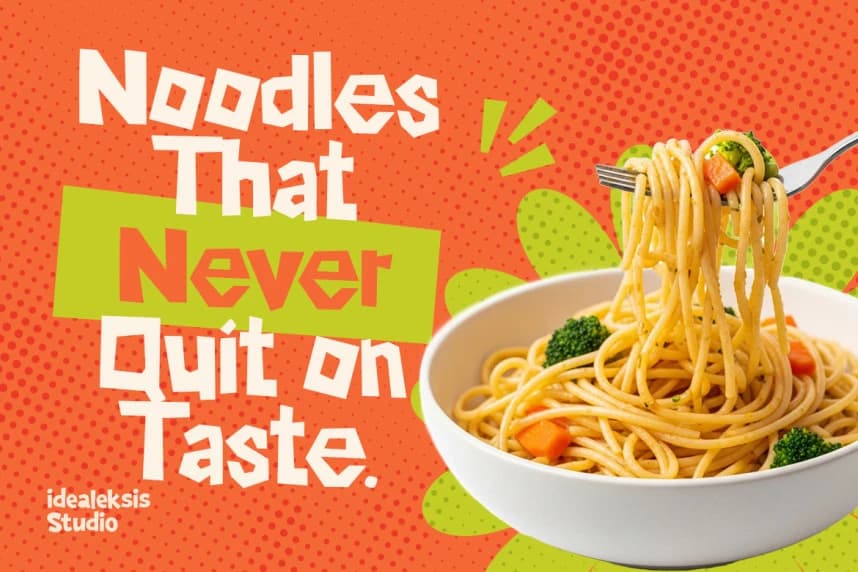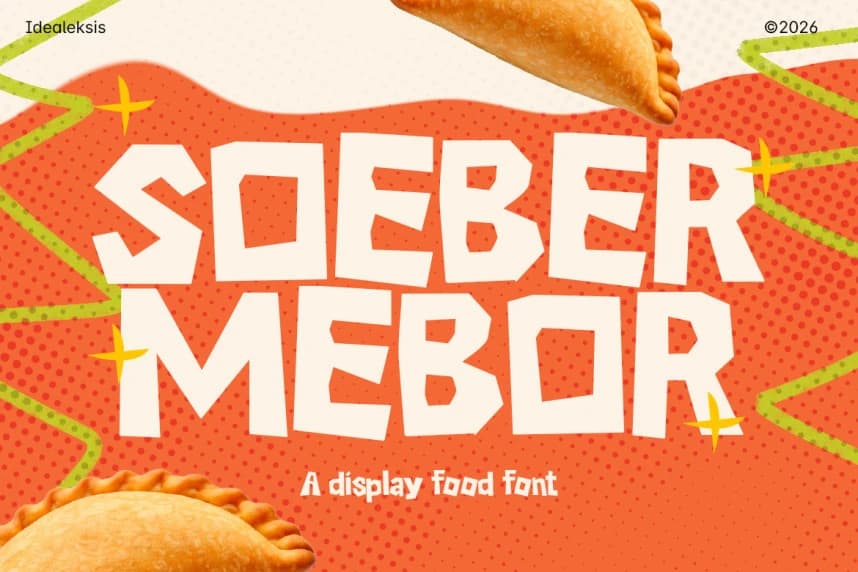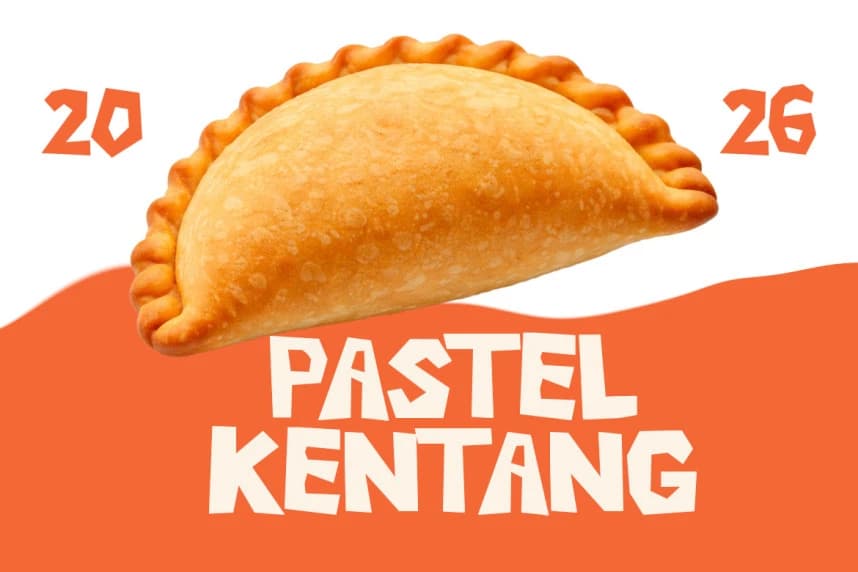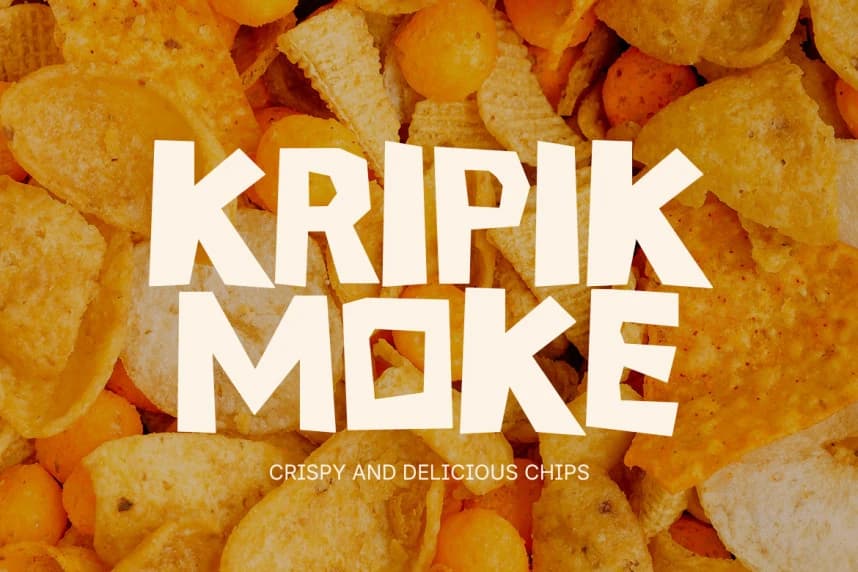
Kalın ve iri bir gösteri tipi olan bu yazı stili, düzensiz, elle kesilmiş geometrik şekillerle karakterize edilir. Harf biçimleri ağır bir kalınlığa sahip olup uçlar keskin ve köşeli, çizgi kalınlıkları ise düzensizdir.
Soeber Mebor – Food Font - Düzensiz, elle kesilmiş geometrik şekillerle karakterize edilen gösterim yazı tipi, kalın ve iri bir görünüme sahiptir. Harf biçimleri ağır bir kalınlığa sahip olup keskin, köşeli uçlar ve düzensiz çizgi kalınlıkları gösterir